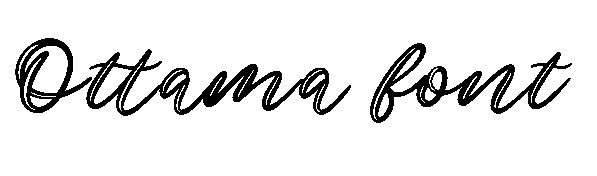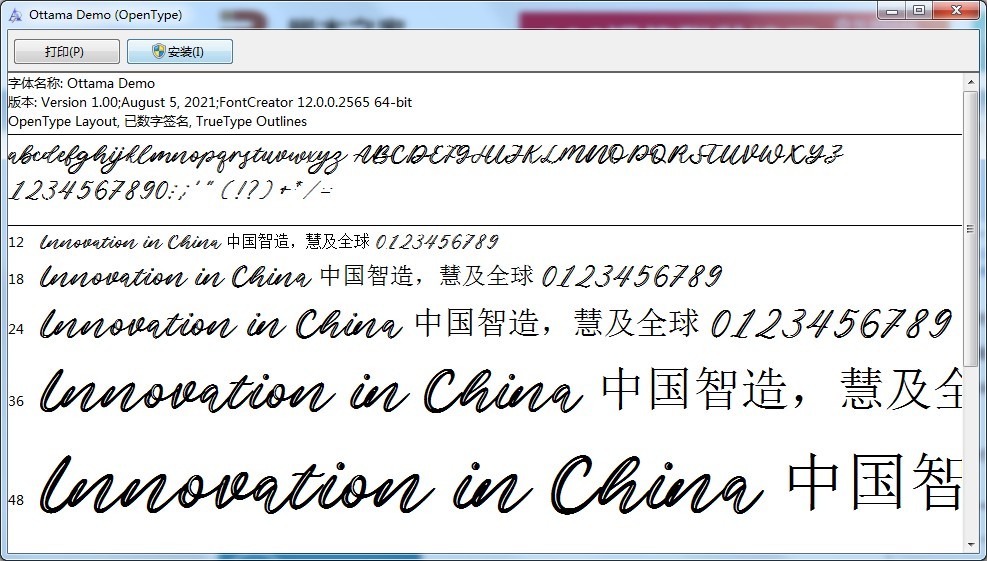
ottama font free藝術(shù)感極強(qiáng)的英文字體,在日常使用字體的過程中大多數(shù)都是用的比較正式的英文體,當(dāng)我們想要設(shè)計一些海報或是制作自己的個性文本時就可以借助該字體來得到獨(dú)特新穎的是視覺效果。
Ottama字體是一款適用于廣告設(shè)計方面的字體,十分的具有藝術(shù)感。